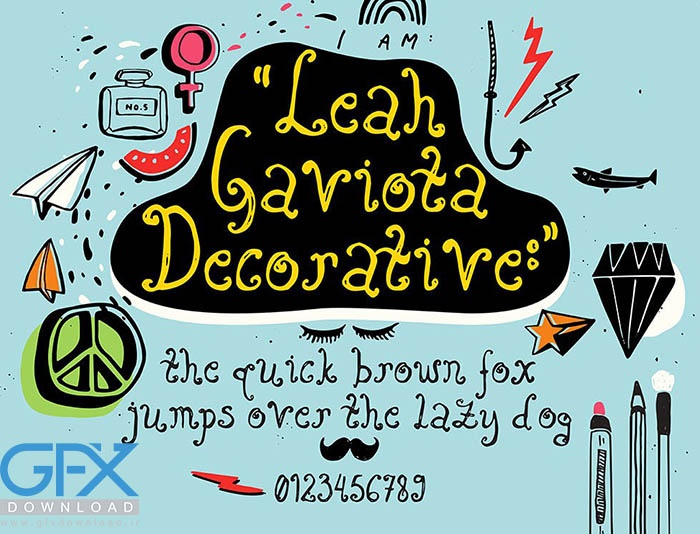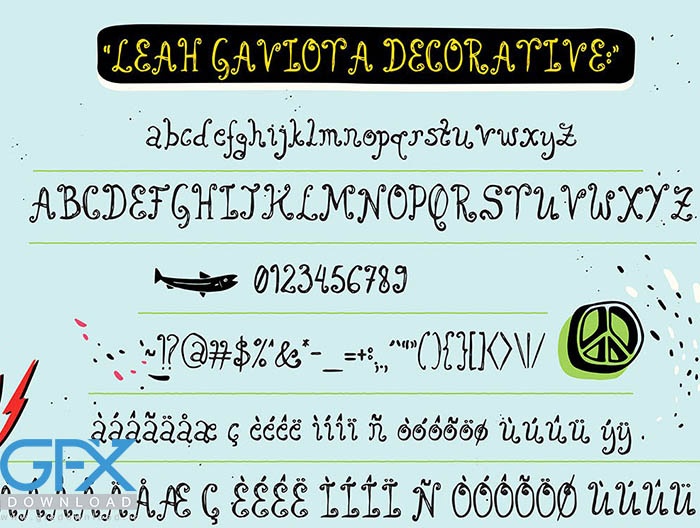
فونت انگلیسی Leah Gaviota
Leah Gaviota ترکیبی از چندین نوع فونت است: اسکریپت، پررنگ، serif و sans-serif، که می‌توانید از آن برای ایجاد یک اثر معمولی و حرفه‌ای استفاده کنید. دانلود رایگان فونت Leah Gaviota با 6 ظاهر متفاوت، برای امضا، عنوان کارت تبریک، نشان و برچسب، آرم و آدرس ، طراحی وب و متن، طراحی جلد و غیره بهترین است، این فونت با حروف برجسته برای زبان بین‌المللی ارائه می‌شود (تصاویر پیش‌نمایش را بررسی کنید تا ببینید کدام حروف‌ها گنجانده شده‌اند).
• در خانواده: پررنگ، دوتایی، نازک، خطی، تزئینی، و طرح کلی
• قلم طراحی شده با دست
• گلیف های تاکیدی